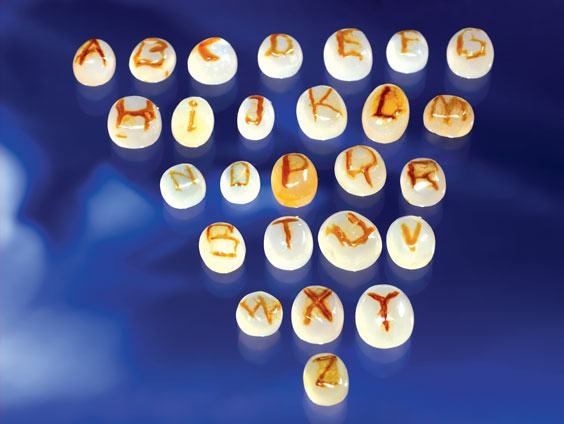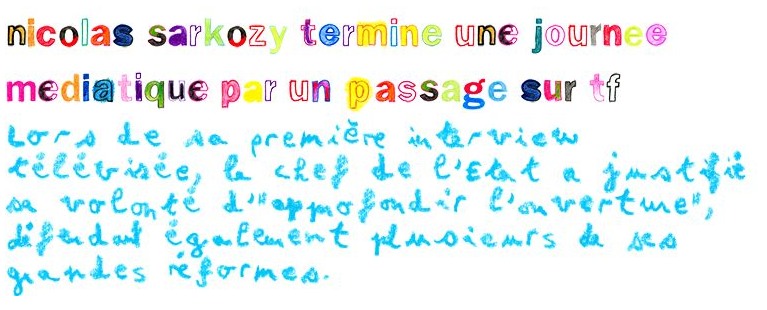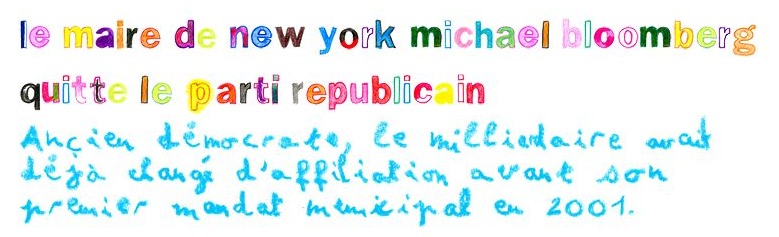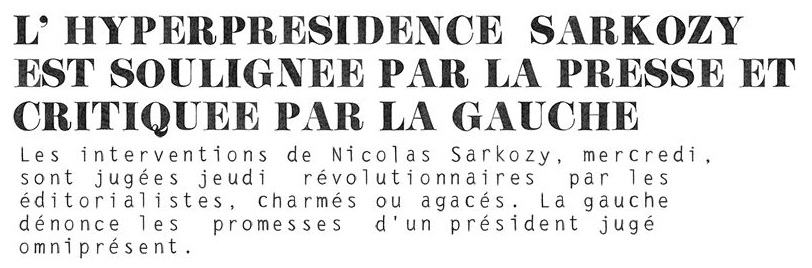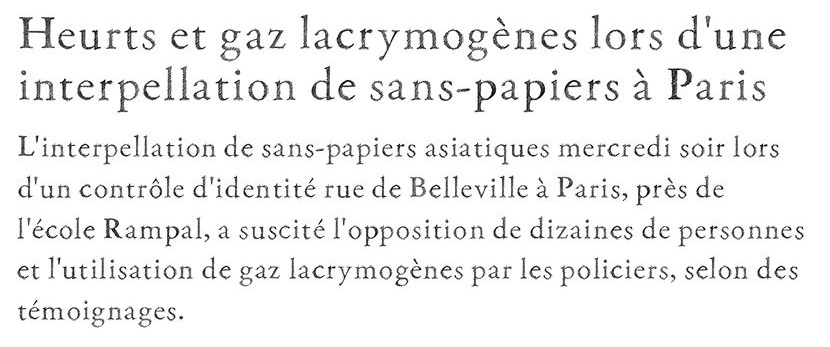
Via Coudal , je découvre ces agates gravées à grand’peine durant plusieurs années. Un tour de force paraît-il… voire… le prix certainement… et pas besoin de FontLab ;-)
Les titres qui suivent ici, sont bien plus intéressants:
Ils proviennent d’un site «http://www.fontself.com/demo/newsmaker_en.php » Via TypeForYou . qu’on peut qualifier d’expérimental tant par le propos d’agrégateur rss que par l’idée qu’on puisse donner à l’information une forme typographique détachée des signifiants originels. Qui a dit que la typo ne fait pas sens? Il suffit d’aller cliquer sur les différentes sources RSS des grands journaux du moment et de choisir son «type» pour l’affichage des grands titres. Vous vivrez une expérience du décalé, de l’impertinence faite typographie… Ça vaut tous les canards déchainés de l’hexagone. Mais je vous laisse juge et avocat… dans vos commentaires.